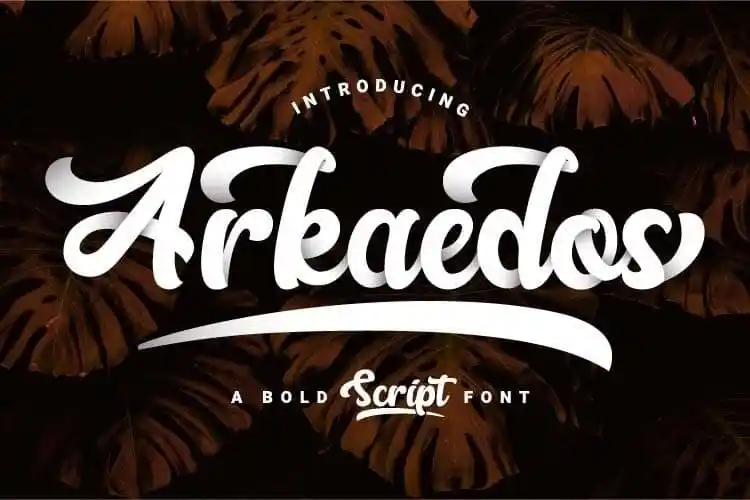
A Arkaedos Script Font é uma elegante tipografia script que transmite uma impressionante força e sofisticação. Este tipo criado pelo designer Prioritype traz consigo um estilo inovador, com linhas distintas e contornos aguçados. A Arkaedos tem um aspecto clássico e singular, ideal para aplicações em variados meios gráficos. De origem vintage até as mais modernas plataformas digitais, a Arkaedos Script se destaca como uma escolha perfeita para elementos visuais que buscam um equilíbrio entre classe e originalidade. Aplicável desde logotipos antigos até peças de design digital, como etiquetas de rótulos de alimentos, embalagens de produtos, marcas de marca, materiais publicitários ou capas para discos musicais. A Arkaedos é a escolha perfeita para designers e criativos que buscam transmitir um visual distintivo em suas obras. Seja através da tipografia dos logos de marcas antigos até os novos cenários digitais, o estilo forte e moderno desta fonte promete acrescentar profundidade ao seu trabalho.